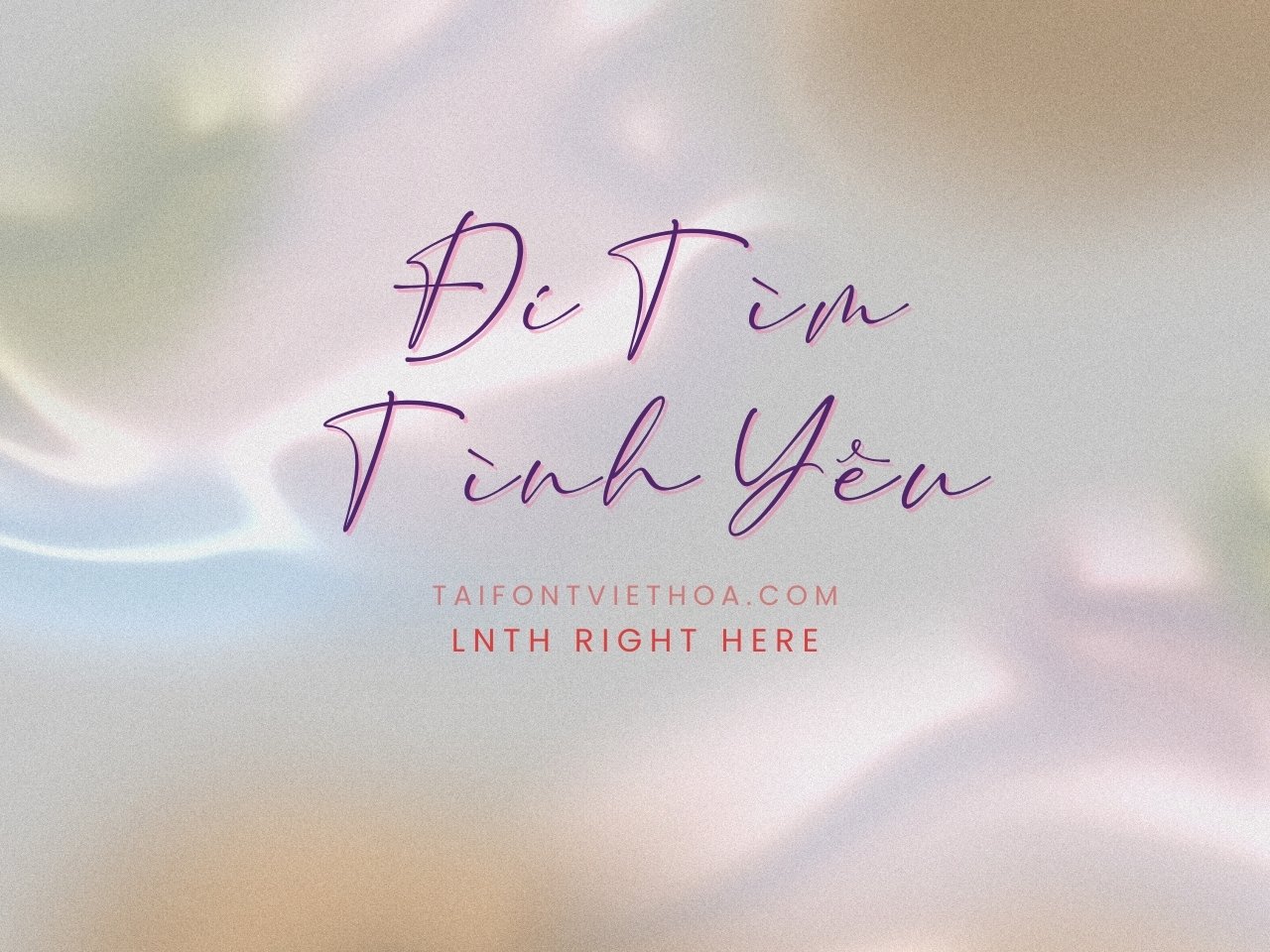
Font việt hóa LNTH Right Here
Giới thiệu về font LNTH Right Here – Ngẫu hứng, tươi vui và đậm chất cá nhân
LNTH Right Here là phiên bản Việt hóa của kiểu chữ viết tay thủ công do Nowhere Std thiết kế – mang phong cách trẻ trung, ngẫu hứng và giàu biểu cảm. Các đường nét tự nhiên và phá cách của font giúp thể hiện cảm xúc trực diện, gần gũi như những dòng ghi chú cá nhân. Tuỳn Pucca đã thực hiện Việt hóa trọn bộ, hỗ trợ tiếng Việt đầy đủ cùng hơn 60 ngôn ngữ khác trên thế giới, giúp font trở nên linh hoạt trong các dự án đa quốc gia.
Đặc điểm thiết kế và ứng dụng nổi bật của LNTH Right Here
LNTH Right Here mang phong cách handwritten – các chữ cái được thiết kế như thể được vẽ tay bằng bút dạ. Nét chữ mềm mại, không tuân theo quy luật cứng nhắc, tạo cảm giác thoải mái, vui tươi và thân thiện. Các ký tự có độ cao không đồng đều, khoảng cách tự nhiên – tạo nên cá tính riêng biệt cho mỗi dòng văn bản.
Font phù hợp với các ngành nghề như thủ công mỹ nghệ, giáo dục mầm non, ẩm thực sáng tạo, spa handmade hoặc các thương hiệu cá nhân hóa. Các ứng dụng thực tế gồm: thiệp sinh nhật, typography Trung Thu, thiết kế poster Valentine, bìa sổ tay, nhãn sản phẩm thủ công, hoặc các nội dung mạng xã hội cần phong cách dễ thương và thu hút giới trẻ.